2つ以上の文字の組み合わせをまとめてデザインしたものを合字(リガチャ)と呼びます。図の例では、fとtが並んだときのくっつき加減の微妙さを、まとめてデザインすることによって解決しています。ftの横画をつなげるだけでなく、tの頭のカット角度も変えてありますね。
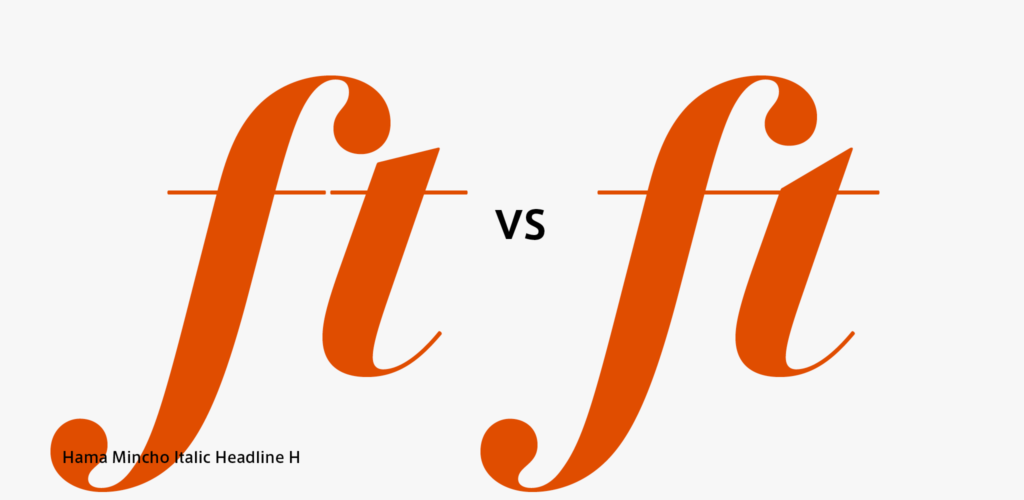
欧文合字はデフォルトでオンになっているアプリケーションも多いため、図に掲載したHama Mincho Italicの場合、原則として合字を使ってもらった方がよさそうな組み合わせとして、fi、fl、Wh、ff、ffi、ffl、fftで、欧文合字(liga)機能を利用しています。